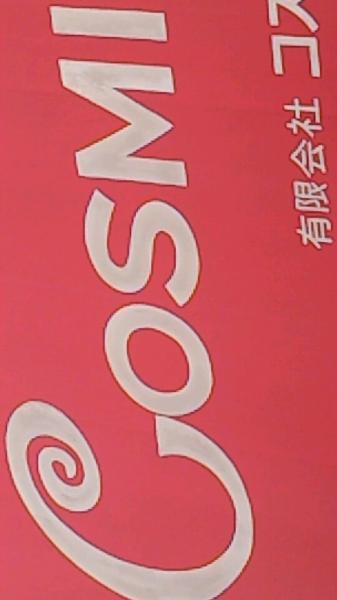
「小」金井市の「Co」、「コ」ミュニティバスの「Co」、「こころ」=CoCoろの通うバスという意味です。
はしっこ 欠けてしまった・・・。
かつて住んでいた町を懐かしんで・・・。
東京新聞見ました。面白そうで、
使ってみたい!と思い連絡しました。
現在アメリカに在住していますが、日本へ帰るたびに、必ず1,2日は吉祥寺で過ごします。このフォントを、活用してみたいと考えています。
東京新聞で拝見しました。フォントが好きなので、